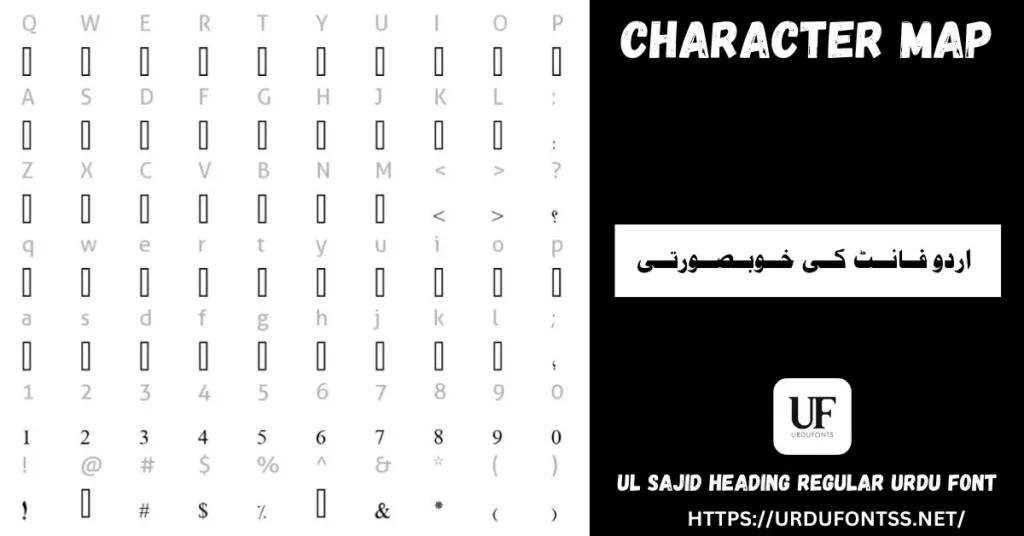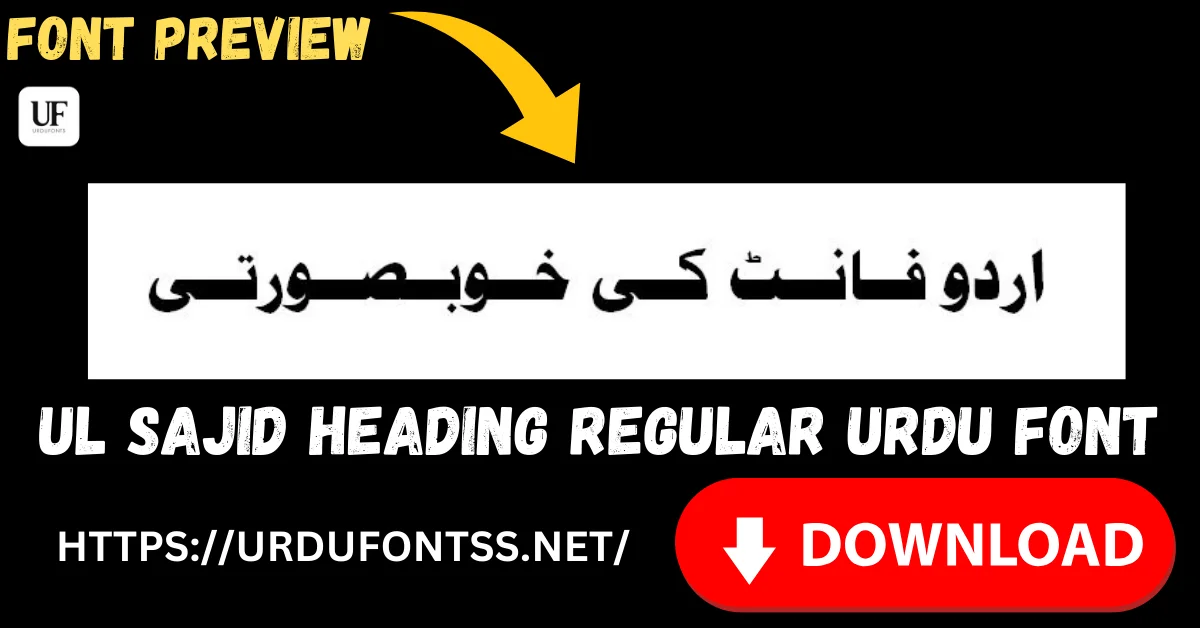
UL Sajid Heading Regular Font – Perfect Bold Urdu Ttf for Stunning Headlines & Titles
What is UL Sajid Heading Regular Font?
agar aap apne Urdu projects ke liye ek bold, clean aur professional heading font dhund rahe ho, to aaj main aapko ek solid choice ke baare mein bataane wala hoon — UL Sajid Heading Regular Font. yeh koi aam Urdu font nahi hai, yeh specially headings, titles aur short highlighted text ke liye design kiya gaya hai.
Aap soch rahe honge, heading font aur normal font mein farq kya hai?” To suniye — heading fonts bold aur attention-grabbing hote hain, lekin saath hi readable bhi hone chahiye. UL Sajid Heading Regular exactly yahi karta hai. Iski styling itni balanced hai ke aapki Urdu text ko standout look deti hai, lekin parhne mein bhi aasaani hoti hai.
Why This Font Stands Out for Headings?
Dekho sister, market mein bohot saare Urdu fonts hain. Lekin heading ke liye font choose karna tricky hota hai — zyada bold ho to ajeeb lagta hai, zyada patla ho to heading ka purpose hi khatam. UL Sajid Heading Regular is balance ko perfectly hit karta hai:
- Bold enough to grab immediate attention
- Clean enough to stay readable even at larger sizes
- Traditional Urdu aesthetics ke saath modern simplicity ka combo
Who Should Use UL Sajid Heading Regular Font?
Ab aap soch rahe honge, “Bhai, yeh font mere liye hai bhi ya nahi?” To ruko, main clear kar deta hoon. Yeh font un sab ke liye hai jo Urdu mein kaam karte hain aur apne headings ko standout look dena chahte hain:
Graphic Designers
Web Developers & Bloggers
Students & Educators
Presentations, assignments, educational posters — student life mein Urdu headings ka kaam aata hi rehta hai. UL Sajid Heading Regular aapke projects ko extra professional touch dega.
Print Media Professionals
Why UL Sajid Heading Regular is a Reliable Choice?
Suniye, main aapko chaar solid reasons deta hoon ke UL Sajid Heading Regular kyun ek reliable font hai:
Top 6 Use Cases of UL Sajid Heading Regular Font
Main ginwa nahi sakta kitni jagah yeh font use ho sakta hai, lekin top 6 bata deta hoon:
- YouTube Thumbnails & Video Titles: Bold Urdu heading se thumbnail click-worthy banti hai. Related: Best Urdu Fonts for YouTube Thumbnails
- Social Media Banners: Instagram, Facebook cover photos — professional look guaranteed
- Educational Presentations: Title slides aur section headings ke liye perfect
- WordPress Blog Headings: Featured text, H1-H2 headings ke liye smooth styling
- Print Posters, Flyers & Billboards: Large format printing mein bhi clarity barkarar. Related: Best Urdu Fonts for Billboards & Digital Signage